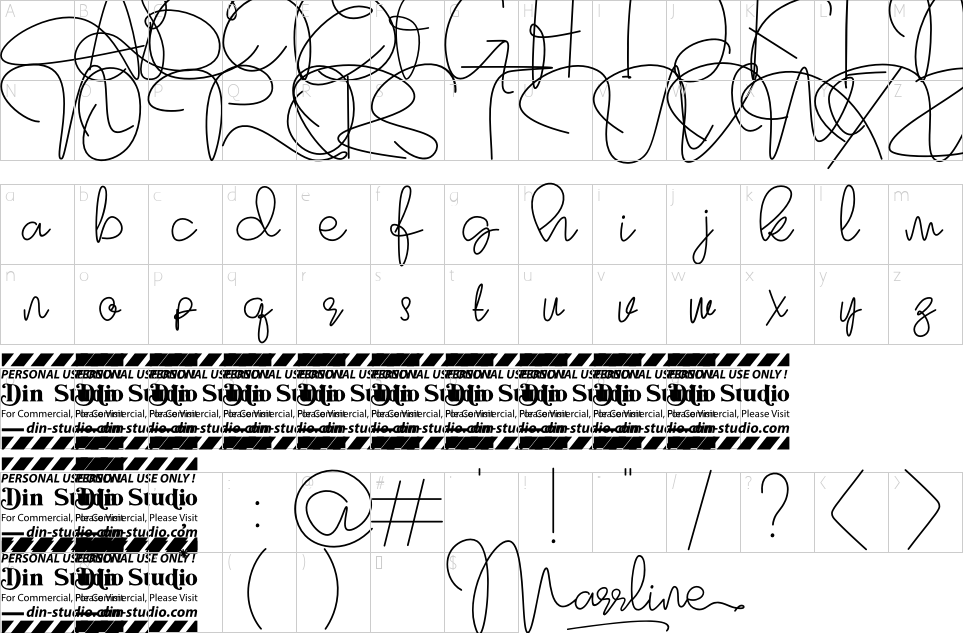
Desculpe pela confusão, mas não há descrição original disponível em português para a font ‘Marrline’. A descrição original é em inglês e não menciona nenhuma característica específica da fonte em português. No entanto, podemos elaborar uma descrição informativa e envolvente em português para a página de download desta fonte. ‘Para os amantes do belo e do elegante, a fonte Marrline oferece um conjunto de linhas sutis e elegantes que podem transformar qualquer texto em uma obra de arte. Desenvolvida pelo Din Studio, essa fonte de alta qualidade foi projetada para oferecer uma experiência visual agradável em ambientes digitais, sejam eles Windows ou Mac. Com mais de 2.400 downloads, Marrline é uma fonte que merece ser explorada e experimentada. Seja para projetos de design editorial, publicidade ou até mesmo para um simples relatório de trabalho, esta fonte oferece uma solução versátil e profissional. Descubra a beleza e a simplicidade da Marrline, onde cada letra se torna uma paixão em si mesma.’